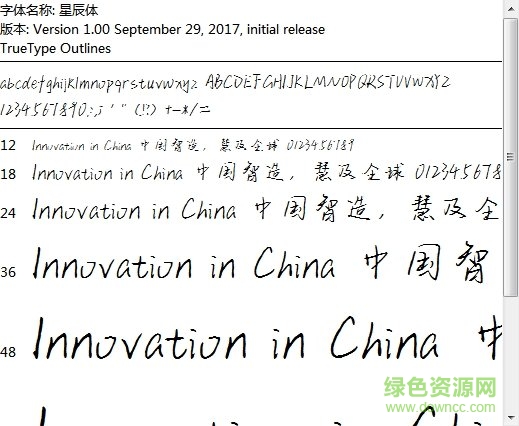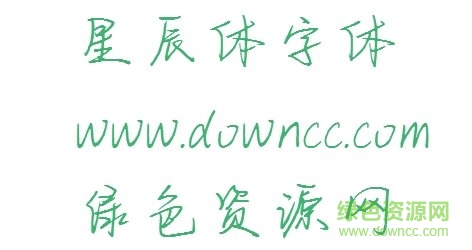
星辰體ttf
星辰體字體ttf有著簡潔清秀的筆觸,給人淡泊深遠(yuǎn)的感覺,如同星辰般令人向往,讓你的設(shè)計更有獨特魅力,綠色資源網(wǎng)誠意推薦!
星辰體是一款字跡清爽、濃淡適宜的手寫字體,給人星空般的高遠(yuǎn)和淡泊體驗,給你的文字更多個性色彩,可以廣泛運用在平面設(shè)計、海報創(chuàng)意等場合